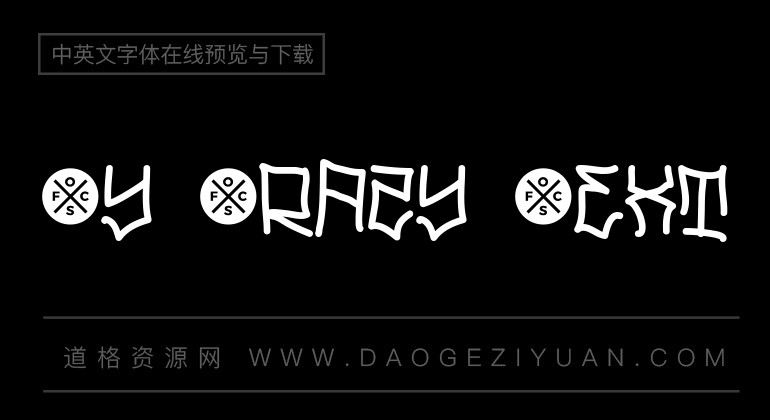
My Crazy Text
My Crazy Text 是一种具有独特风格的字体,常用于制作海报、广告、宣传品等视觉设计中。该字体的特点在于字母形态极具变幻性和奇特性,给人一种疯狂、不羁、夸张的感觉。 该字体的字母形态各异,有的字母甚至被设计成了弯曲的形状,使得整个字体看起来很有趣味性和视觉冲击力。My Crazy Text 字体还有许多变体,如加粗、倾斜、扭曲等等,可以让设计师更灵活地运用该字体。 总的来说,My Crazy Text 字体适用于需要突出个性和独特性的场合,可以作为视觉设计中的重要元素,吸引人们的注意力,提高宣传效果。
My Crazy Text是一款非常不错的手写艺术字体,具有很好的视觉感,适合于文化类的宣传设计、商业类品牌的广告和产品包装设计以及个性化文字排版等较多场景。